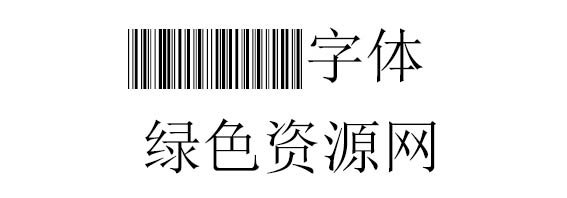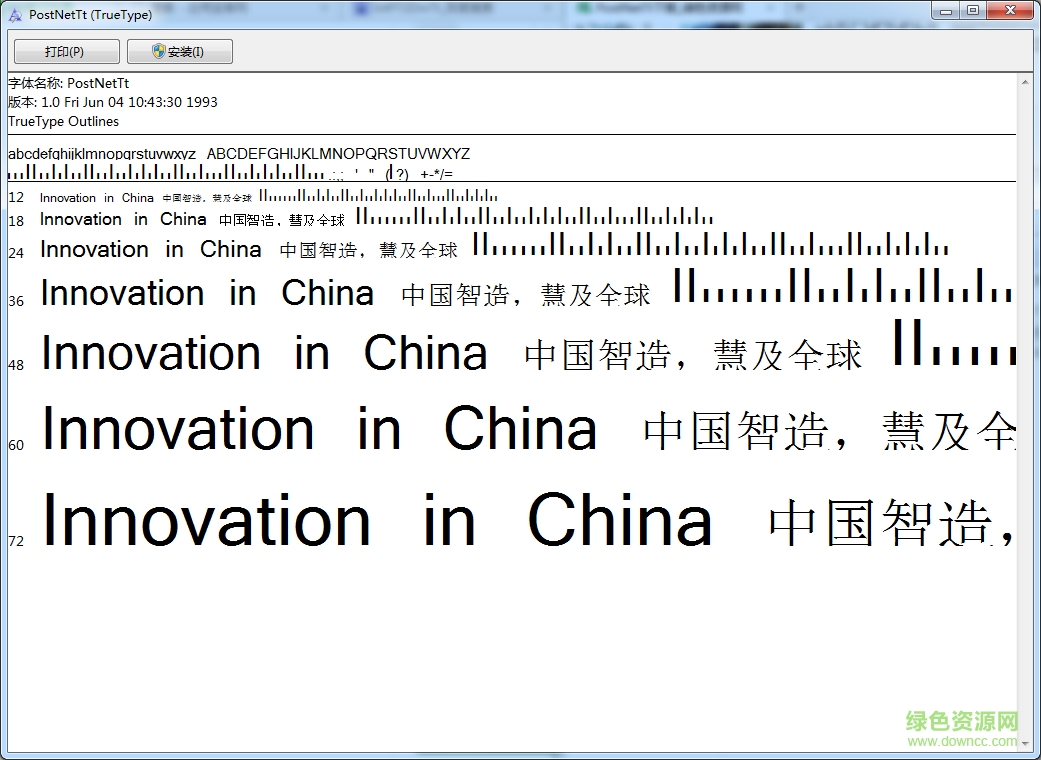
PostNetTt是一款大家都在用的條形碼字體軟件,字體顯示簡(jiǎn)潔大方,支持漢子數(shù)字拼音等多種方式輸入,條形碼顯示獨(dú)具特色。快來(lái)綠色資源網(wǎng)下載體驗(yàn)吧!
PostNetTt字體是一種獨(dú)特的條形碼字體,將文字轉(zhuǎn)換成條形碼的形式呈現(xiàn)在用戶眼前